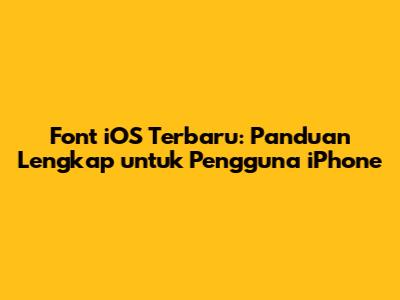
Hey guys! Kalian para pengguna iPhone pasti sering banget kan bosen dengan tampilan font yang itu-itu aja? Nah, kali ini kita bakal bahas tuntas tentang font iOS terbaru dan gimana caranya bikin tampilan iPhone kalian jadi lebih fresh dan menarik. Gak cuma itu, kita juga bakal kasih tau tips dan trik seputar font yang mungkin belum kalian tau. So, stay tuned dan simak terus artikel ini ya!
Mengapa Font di iOS Itu Penting?
Mungkin sebagian dari kalian bertanya-tanya, kenapa sih kita perlu repot-repot mikirin font di iOS? Bukannya yang default udah cukup bagus? Well, sebenarnya ada beberapa alasan kenapa font iOS terbaru itu penting banget untuk diperhatikan. Pertama, font itu adalah salah satu elemen visual yang paling berpengaruh dalam sebuah desain. Dengan memilih font yang tepat, kalian bisa mengubah keseluruhan mood dan feel dari tampilan iPhone kalian.
Bayangin aja, guys. Kalian lagi bikin presentasi penting, tapi font yang kalian pake malah Comic Sans. Kan gak lucu. Sama halnya dengan iPhone. Kalau font yang kalian pake gak sesuai dengan kepribadian atau gaya kalian, ya kurang maksimal aja gitu. Kedua, font juga bisa mempengaruhi readability atau keterbacaan teks. Font yang jelas dan mudah dibaca tentu akan membuat pengalaman menggunakan iPhone jadi lebih nyaman. Gak mau kan mata kalian cepet lelah cuma karena fontnya terlalu kecil atau terlalu aneh?
Ketiga, dengan mengganti font iOS terbaru, kalian bisa menunjukkan identitas diri kalian. iPhone itu kan udah kayak personal statement gitu ya. Dengan mengganti font, kalian bisa bikin iPhone kalian jadi lebih unik dan beda dari yang lain. Jadi, jangan ragu untuk eksplorasi berbagai macam font dan temukan yang paling cocok dengan kalian. Intinya, font di iOS itu bukan cuma sekadar hiasan. Lebih dari itu, font adalah bagian penting dari pengalaman menggunakan iPhone yang bisa kalian optimalkan untuk berbagai kebutuhan.
Fitur Font Bawaan iOS yang Perlu Kamu Ketahui
Sebelum kita bahas tentang cara mengganti font iOS terbaru, ada baiknya kita kenalan dulu dengan fitur font bawaan yang ada di iOS. Apple sendiri udah menyediakan beberapa pilihan font yang bisa kalian gunakan secara default. Salah satunya yang paling terkenal adalah San Francisco. Font ini dirancang khusus untuk perangkat Apple dan dikenal karena readability-nya yang tinggi. San Francisco hadir dalam beberapa varian, mulai dari Regular, Bold, hingga Italic. Kalian bisa memilih varian yang paling sesuai dengan preferensi kalian.
Selain San Francisco, ada juga beberapa font lain yang bisa kalian temukan di iOS, seperti Helvetica Neue, Arial, dan Times New Roman. Meskipun pilihan font bawaan ini terbilang cukup terbatas, tapi sebenarnya kalian masih bisa memaksimalkannya dengan berbagai cara. Misalnya, kalian bisa mengatur ukuran font sesuai dengan kebutuhan kalian. Caranya gampang banget, tinggal masuk ke Settings > Display & Brightness > Text Size. Di situ, kalian bisa geser slider untuk mengatur ukuran font sesuai dengan yang kalian inginkan. Selain itu, kalian juga bisa mengaktifkan fitur Bold Text untuk membuat teks jadi lebih tebal dan mudah dibaca. Fitur ini juga bisa kalian temukan di Settings > Display & Brightness > Bold Text. Dengan mengaktifkan fitur ini, semua teks di iPhone kalian akan ditampilkan dengan huruf tebal, termasuk di aplikasi, menu, dan notifikasi. Jadi, meskipun pilihan font iOS terbaru bawaan terbatas, kalian tetap bisa mengoptimalkannya untuk mendapatkan pengalaman membaca yang lebih baik.
Cara Mengganti Font di iOS (Tanpa Jailbreak!)
Nah, sekarang kita masuk ke bagian yang paling ditunggu-tunggu: cara mengganti font iOS terbaru tanpa perlu jailbreak! Mungkin sebagian dari kalian udah tau bahwa iOS itu sistem operasi yang cukup ketat dalam hal customization. Jadi, mengganti font secara langsung itu memang gak semudah di Android. Tapi, jangan khawatir! Ada beberapa trik yang bisa kalian lakukan untuk tetap bisa mengganti font di iPhone kalian.
Salah satu caranya adalah dengan menggunakan aplikasi pihak ketiga. Di App Store, ada banyak banget aplikasi yang menawarkan fitur custom font. Beberapa di antaranya bahkan gratis! Tapi, perlu diingat ya guys, gak semua aplikasi custom font itu aman dan terpercaya. Jadi, sebelum kalian mengunduh dan menginstal aplikasi, pastikan untuk membaca review dan rating-nya terlebih dahulu. Pilih aplikasi yang punya reputasi baik dan banyak direkomendasikan oleh pengguna lain. Setelah kalian menemukan aplikasi yang terpercaya, kalian bisa langsung mengunduhnya dan mengikuti petunjuk yang diberikan. Biasanya, aplikasi custom font akan meminta kalian untuk menginstal profile di iPhone kalian. Profile ini berisi informasi tentang font yang akan kalian gunakan. Setelah profile terinstal, kalian bisa langsung memilih font yang kalian inginkan dan menerapkannya ke seluruh sistem iOS kalian. Tapi, perlu diingat bahwa cara ini mungkin gak sepenuhnya mengubah font di semua bagian iOS. Beberapa aplikasi mungkin tetap menggunakan font default. Selain itu, ada juga kemungkinan bahwa aplikasi custom font ini akan memperlambat kinerja iPhone kalian. Jadi, gunakanlah dengan bijak dan pertimbangkan baik-baik sebelum memutuskan untuk menginstal aplikasi custom font. Intinya, meskipun agak tricky, mengganti font iOS terbaru tanpa jailbreak itu masih mungkin dilakukan. Yang penting, kalian harus hati-hati dan teliti dalam memilih aplikasi pihak ketiga.